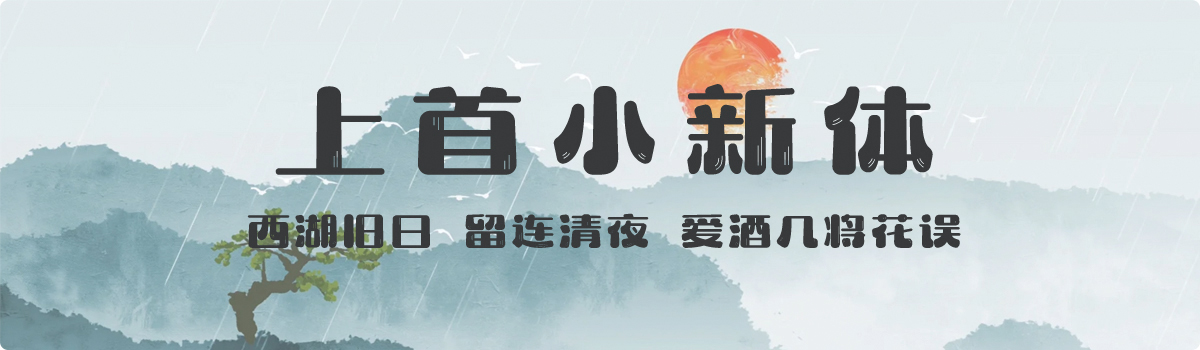
上首小新体
上首小新体,这款字体结构工整、笔画清晰,兼顾美观与易读性,适用于标题、正文、海报、包装、LOGO 等多种场景。字形优雅稳定,风格百搭耐看,适配日常排版与创意设计,让文字呈现更舒适、更具质感。上首小新体一笔一画,皆是细节,以均衡的比例、流畅的线条打造舒适视觉体验,字形端正大气,风格简约现代。无论是商业设计、品牌宣传还是日常排版,都能轻松驾驭,让文字更有格调与力量。上首小新体字体下载。